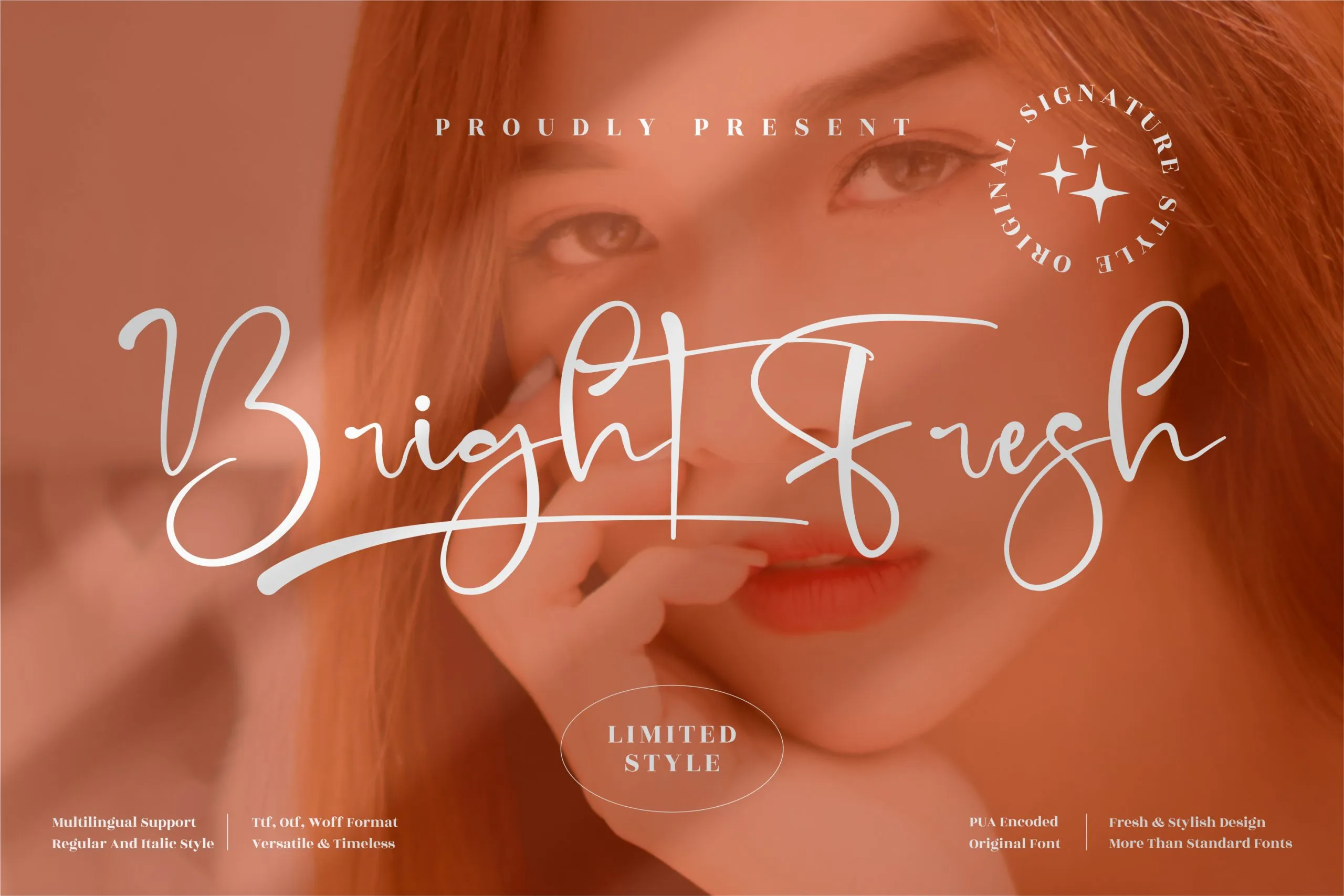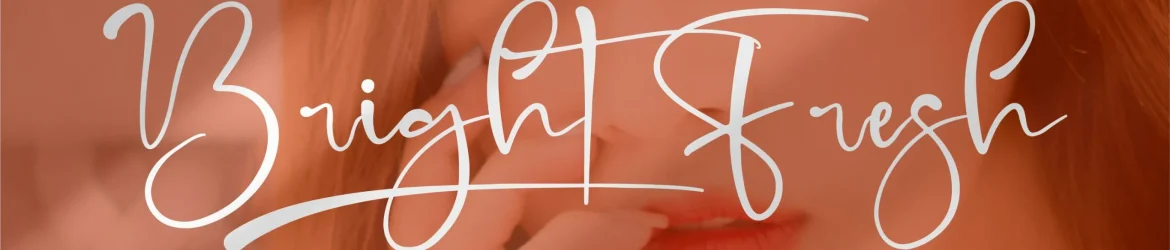
Bright Fresh Font – Download Grátis
A “Bright Fresh Font” é uma elegante fónta assinatura criada pelo designer perspectype para projetos que buscam a qualidade premium. Com seu estilo fresco e moderno, ela se destaca como um recurso perfeito para diversos campos gráficos. Seja você uma empresa desejando criar identidade visual única ou um designer de moda buscando uma fonte especializada para o seu projeto em homewear, embalagens de produtos ou até mesmo a sua própria camiseta personalizada, essa fónta assinatura será um elemento indispensável. Sujeitamente a projetos como logos, identidades visuais, criação de marcas, embalagens de produtos e até mesmo o design da etiqueta de seu produto, esta fonte moderna irá garantir que você tenha um toque de sofisticação em todas as suas criações. Junto com sua versão escrita a mão, “Bright Fresh Font” é perfeitamente adaptada para trabalhos onde cada detalhe importa. Seja ele o design de uma camiseta, uma assinatura no papel ou até mesmo um selo personalizado, esta fonte oferece um toque único e elegante aos seus projetos. Além disso, esta fónta também se destaca como uma escolha ótima para elementos gráficos mais sofisticados. Seja o seu trabalho de fotografia, a sua marca ou até mesmo um selo para eventos especiais, ela oferece os detalhes finais necessários para tornar seu design ainda mais envolvente e impactante. Esta fonte moderna é perfeita para quem busca uma combinação de elegância e frescura em cada projeto. Ela não apenas adicionará um toque personalizado ao seu trabalho, mas também ajudará a destacá-lo no meio do caos visual que o mundo da criatividade produz.